输入一个词,挑一个样式,下载 PNG。就这么简单,大约十秒钟。
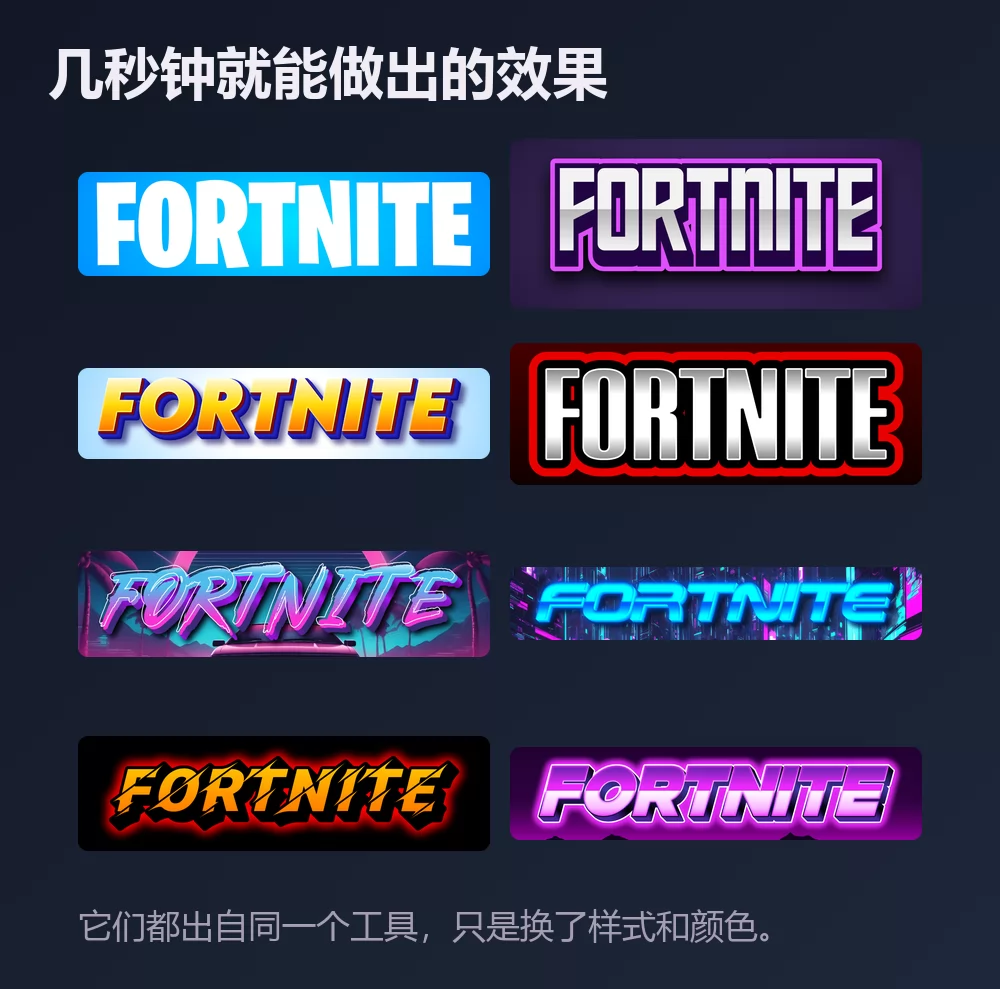
它们都出自同一个堡垒之夜字体生成器,只是在列表里换了样式。无需安装,无需账号。
关于堡垒之夜字体
《堡垒之夜》是 Epic Games 与 People Can Fly 开发的沙盒生存游戏,2017 年 7 月 25 日以付费抢先体验的方式发布,而真正让它成为现象级作品的是随后推出的免费大逃杀模式。
标志所用的字体是 Burbank Big Condensed,由 Tal Leming 设计,使用时做了修改。Burbank 是一款专为这类用途打造的标题字体家族,约有二十种样式。Burbank Big 有三种字宽,每种四个字重;配套的 Burbank Small 专为小字号绘制,有四种字宽,每种都带斜体。
怎样做堡垒之夜文字
第一步:输入文字
打开生成器,把示例文字换成你自己的:昵称、战队标签、频道名称、视频标题。字母会随着输入实时重绘。
第二步:挑一个样式
最经典的是蓝色渐变上厚重的白色窄体大写字母。「样式」标签页可以分别改填充、描边和阴影:字形保留,配色可以带去别处。
第三步:选好尺寸
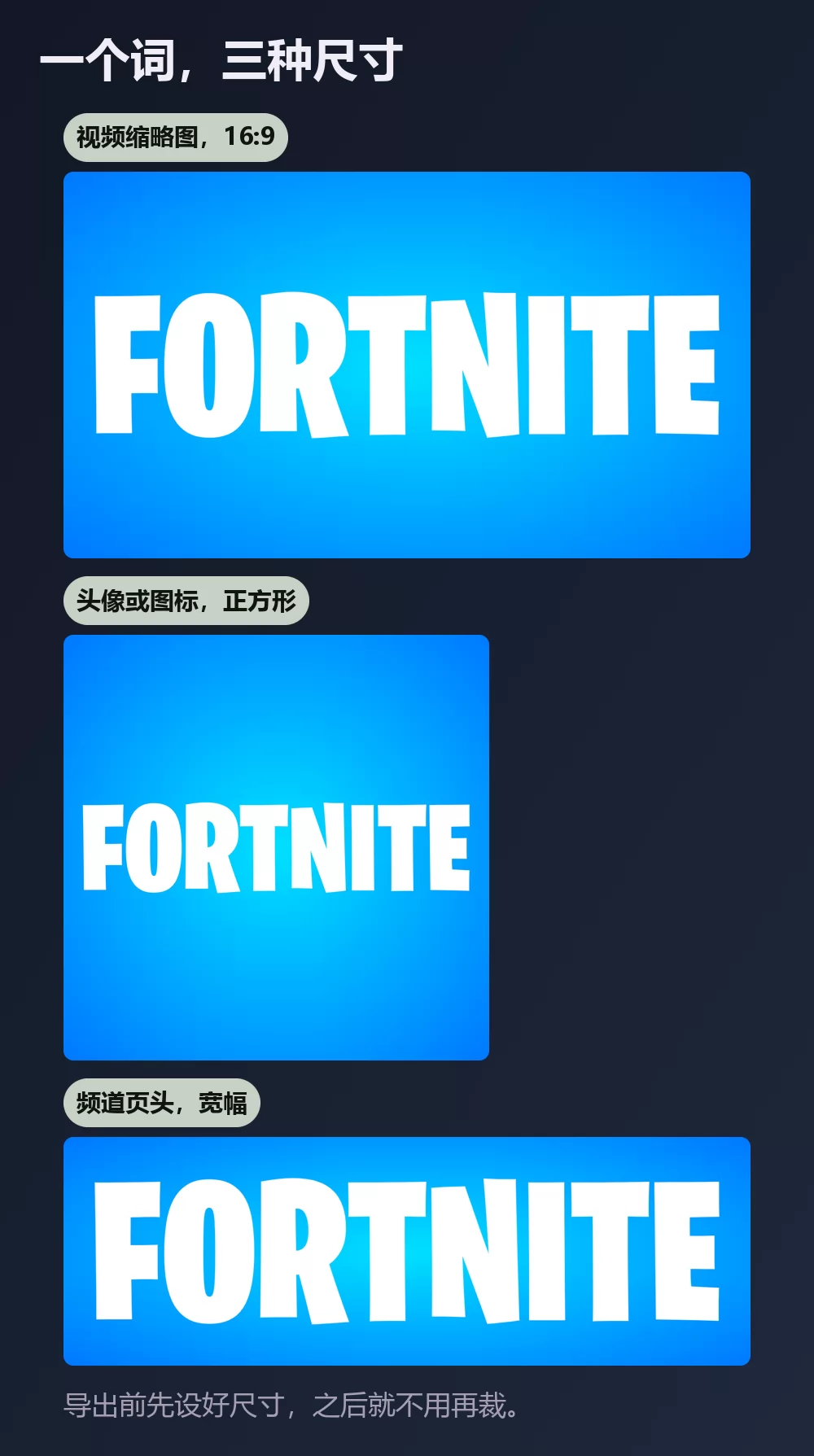
导出前先设好尺寸,之后就不用再裁。视频缩略图用 16:9,头像或图标用正方形,频道页头用宽条。
第四步:下载
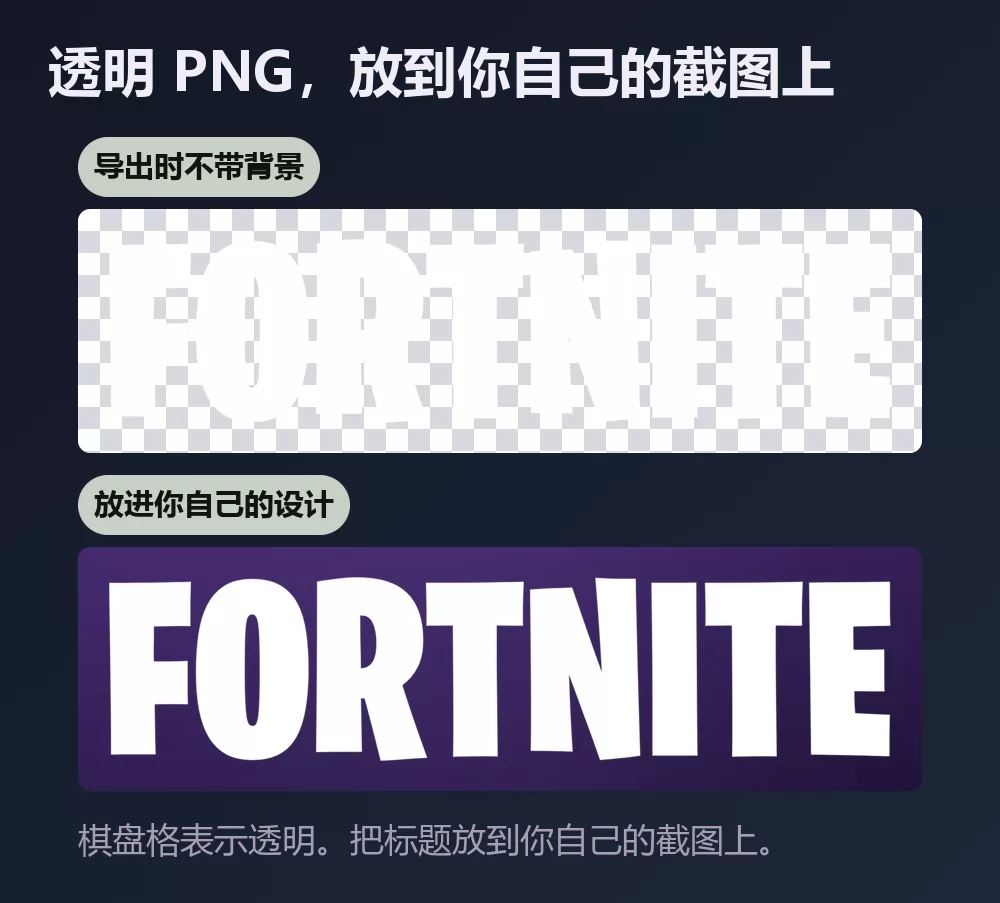
如果打算把标题放到自己的截图上,就在「下载」标签页里选透明 PNG。这个选项多数人会漏掉,而做缩略图时它恰恰最关键:你自己的截图在后,标题在上,周围没有白框。
名字一长,宽度很快就满了
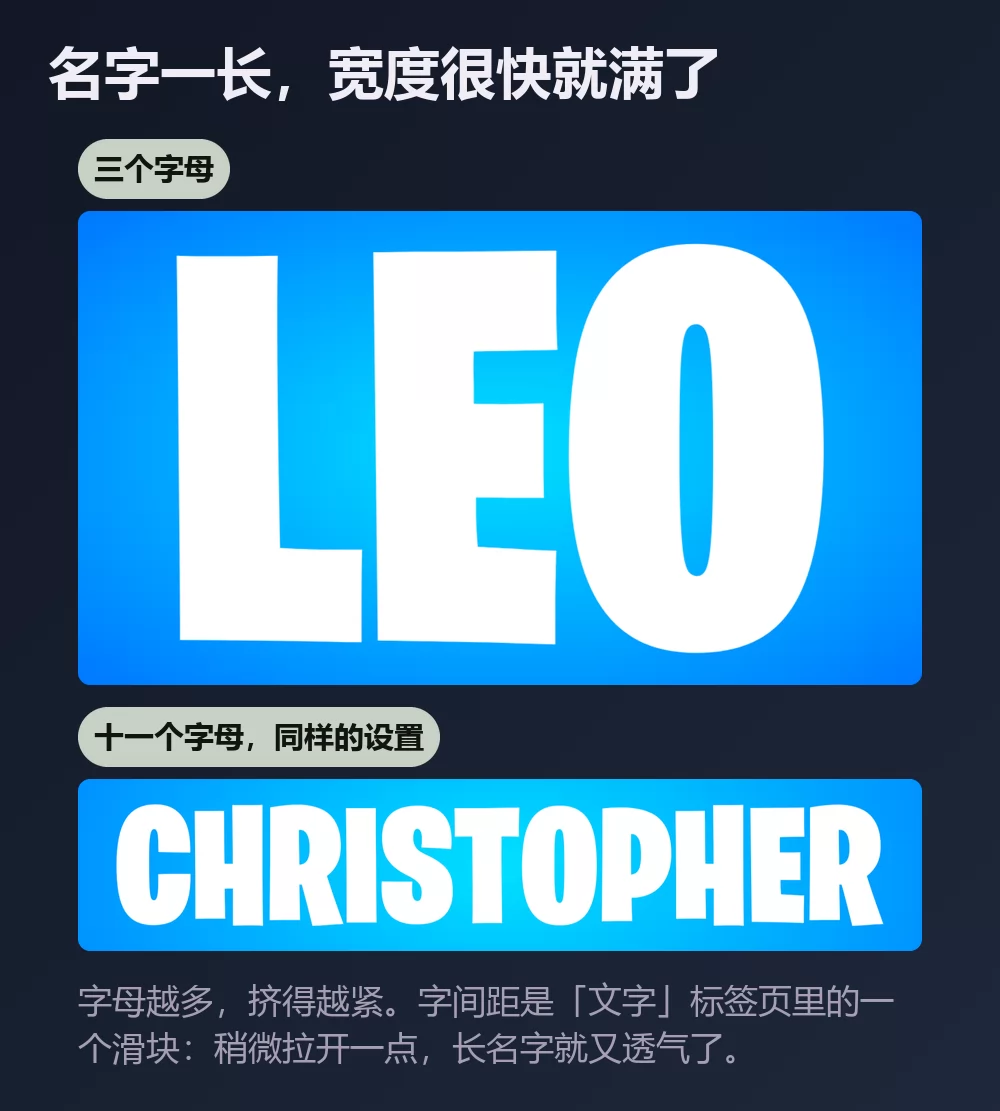
字母越多,挤得越紧。字间距是「文字」标签页里的一个滑块:稍微拉开一点,长名字就不再显得局促。同一个标签页里还有缩放、行距、弯曲和旋转。
标志的样子,还是电竞的样子
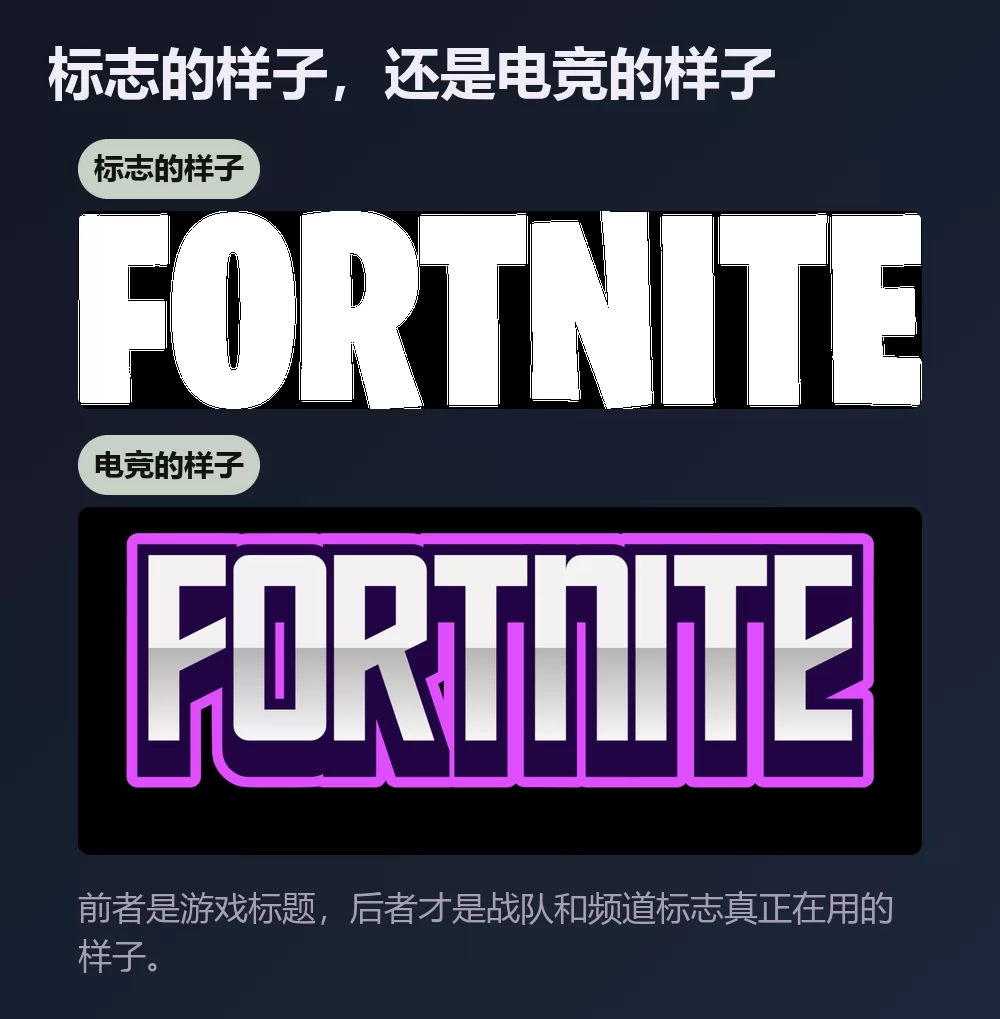
标志的样子就是游戏标题本身:厚重的窄体大写,白色,倾斜一两度。
电竞的样子保留同样的字重,再加上彩色描边和发光。战队标志、频道横幅和赛事图都是这么做的,而且缩到头像大小时,它比一个单纯的白色字标经得住多了。
想装字体的话,该装哪一款
真正接近的免费选择,都是 Google Fonts 上的开放授权字体:
- Anton 单独来看最接近:只有一个字重,非常厚、非常窄,且可免费商用。Canva 里也有。
- Bebas Neue 略轻一点、略窄一点,长期以来都是游戏缩略图的热门选择。
- Oswald 适合需要多个字重而不是单一标题字重的情况。
它们都不是复刻。它们给出的是同样的轮廓,而在缩略图尺寸下,眼睛读到的几乎就是轮廓。
怎样在 Canva 里做堡垒之夜文字
Canva 没有 Burbank,但有 Anton,所以不用离开 Canva 也能做得很接近。至于描边、发光和倾斜,把字样做成透明 PNG 再上传:它可以直接放进 Canva 设计稿,而且保持清晰。
怎样在 Photoshop 里做堡垒之夜文字
装上 Anton 或 Bebas Neue,用大写打好字,再用图层样式把处理效果搭出来:
- 渐变叠加,从浅蓝到更深的蓝,自上而下。
- 描边,设为外部,白色或鲜亮的颜色,加粗。
- 外发光,颜色与描边相同,不透明度调低,范围放宽。
- 投影,收紧且偏暗。
然后把整个文字图层转一到两度。这最后一下很小,却是「一个词」和「一个游戏标志」的分界。
怎样在 Word 里做堡垒之夜文字
装好字体,打好字,再用文字效果做描边和阴影。Word 既做不出真正的外发光,也无法精确地做渐变填充,所以结果会显得很平。凡是缩略图或要发布的东西,导出的 PNG 都会更好看。
在手机上
堡垒之夜字体免费吗?
常见问题
《堡垒之夜》用的是什么字体? Burbank Big Condensed,由 Tal Leming 设计,使用时做了修改。它是商业字体家族。
最接近的免费堡垒之夜字体是哪款? Google Fonts 上的 Anton。Bebas Neue 也很接近,需要多个字重时可以用 Oswald。
Burbank 有多少种样式? 约二十种。Burbank Big 有三种字宽、每种四个字重,Burbank Small 另加四种字宽并配斜体,供小字号使用。
怎样得到透明背景? 在「下载」标签页里选透明 PNG,再把标题放到你自己的截图上。
为什么我做出来的字跟真标志比显得很平? 多半是描边、发光和那点轻微倾斜的问题,而不是字体。这三项比字形更起作用。